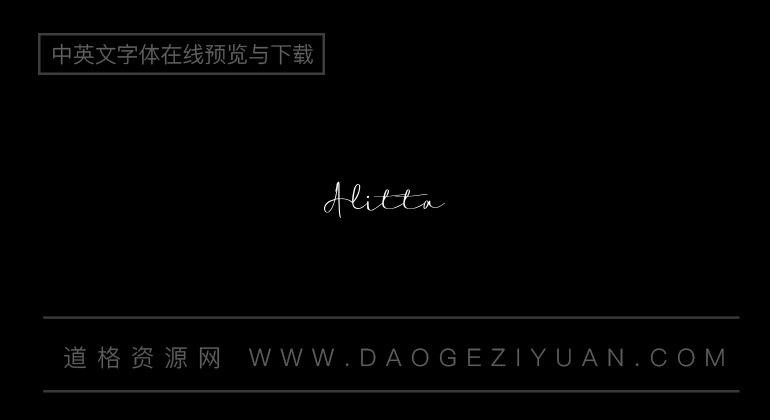
Alitta 字体是一款让人耳目一新的抽象字体,它具有精致而独特的外观,可以帮助创造出更加有趣的文字设计作品。它有一种简约而现代的风格,可以让你的文字内容更加有趣,更加具有吸引力。它有着更加流畅的字形,可以让你的文字内容更加精致。内容介绍
Alitta是一款非常不错的手写艺术字体,具有很好的视觉感,适合于文化类的宣传设计、商业类品牌的广告和产品包装设计以及个性化文字排版等较多场景。